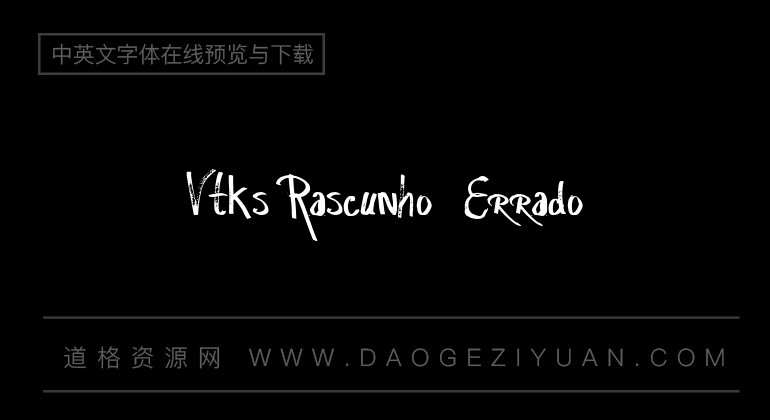
Vtks Rascunho Errado 是一种艺术性质的手写风格字体,具有非常独特的笔画和线条,可以用于各种创意设计和艺术项目中。该字体是由巴西设计师 Douglas Vitkauskas 设计的,其特点在于每个字母都为手写提笔风格,仿佛是一个草稿或错误的初稿。这种字体非常适合用于海报设计、标志和插图等图形设计方面,它可以给作品带来一种艺术感和手工感。除此之外,Vtks Rascunho Errado 也可以用于书籍装帧、宣传册和个人品牌标识等方面。内容介绍
Vtks Rascunho Errado是一款非常不错的手写艺术字体,具有很好的视觉感,适合于文化类的宣传设计、商业类品牌的广告和产品包装设计以及个性化文字排版等较多场景。